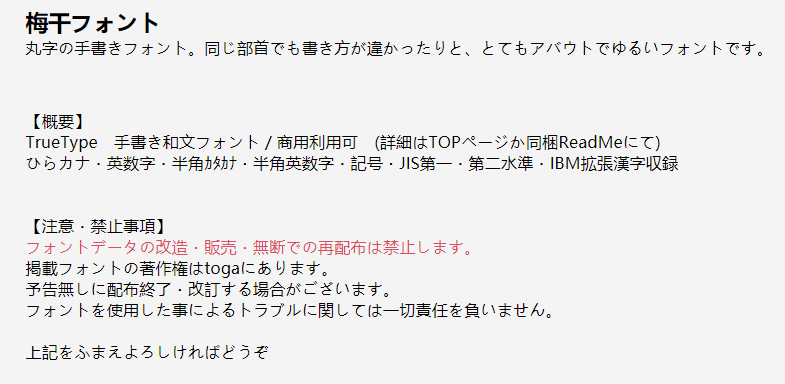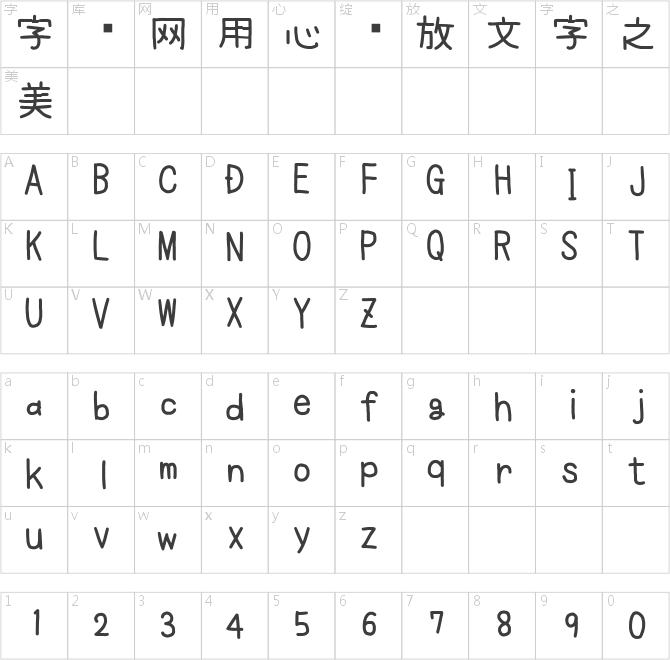
梅干手寫フォントumeboshi 詳情頁
字體名稱: 梅干手寫フォン
梅干手寫體是日本設(shè)計師“toga”先生創(chuàng)建的手寫免費商用字體,精心書寫的圓字非常容易閱讀,非常適合休閑的設(shè)計。
梅干手寫體收錄了平假名、英文數(shù)字、半角·半角英文數(shù)字、符號、JIS第一、第二水準(zhǔn)、IBM擴展?jié)h字。 簡體字?jǐn)?shù)不算多,但是繁體則比較齊全。